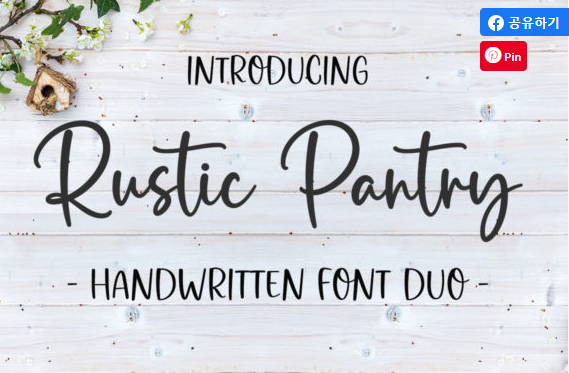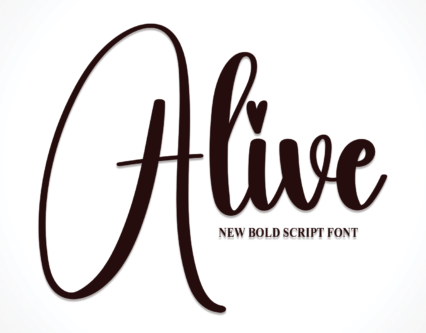
오늘은 제가 최근에 즐겨쓰고 있는
creative fabrica 사이트를 소개하려고 합니다.
크리에이티브 페브리카는
미리캔버스의 제한적인 글씨체와 디자인에 조금
지루함을 느끼던 와중에 알게되어
우리가 좋아하는 캘리그라피 (caligraphy) 스타일의 폰트가 정말 많아서
다 비슷해 보이지만 조금씩 달라서 굉장히 매력적이에요
아래 영문폰트와 그래픽이 디자인을 잘 모르는 사람들도
굉장히 편하게 사용할수 있도록
되어 있어요 ! 요즘 이런 사이트들이 많아서 개인적으로 얼마나 다행인줄 모릅니다.
포토샵과 일러스트를 배웠지만 디자인 감각을 키우려면 도움이 필요한데
이런 사이트들에서 도움을 받으니 굉장히 작업성이 좋은것 같아요
아래 폰트는 특히나 인기많은 영문필기체 폰트입니다.
두번째로 제가 좋아하는 하트가 콕 찍히는 alive font입니다.
이 폰트는 제가 구독을 그만하더라도 개인소장하고 싶을만큼
즐겨쓰는 글씨체에요.
레터링케이크 하시는 분들도 글씨연습할때 따라하시면
너무 이쁠꺼같아요 !
아래 하트 폰트는 너무 신기해서 처음에 설치했는데
하트 이외에도 두들형태의 다양한 이모티콘들이 있어서
따로 그리지 않고 사용하고 있어요
하트도 모양이 다양해서 쓸때마다 한참을 고민해요!